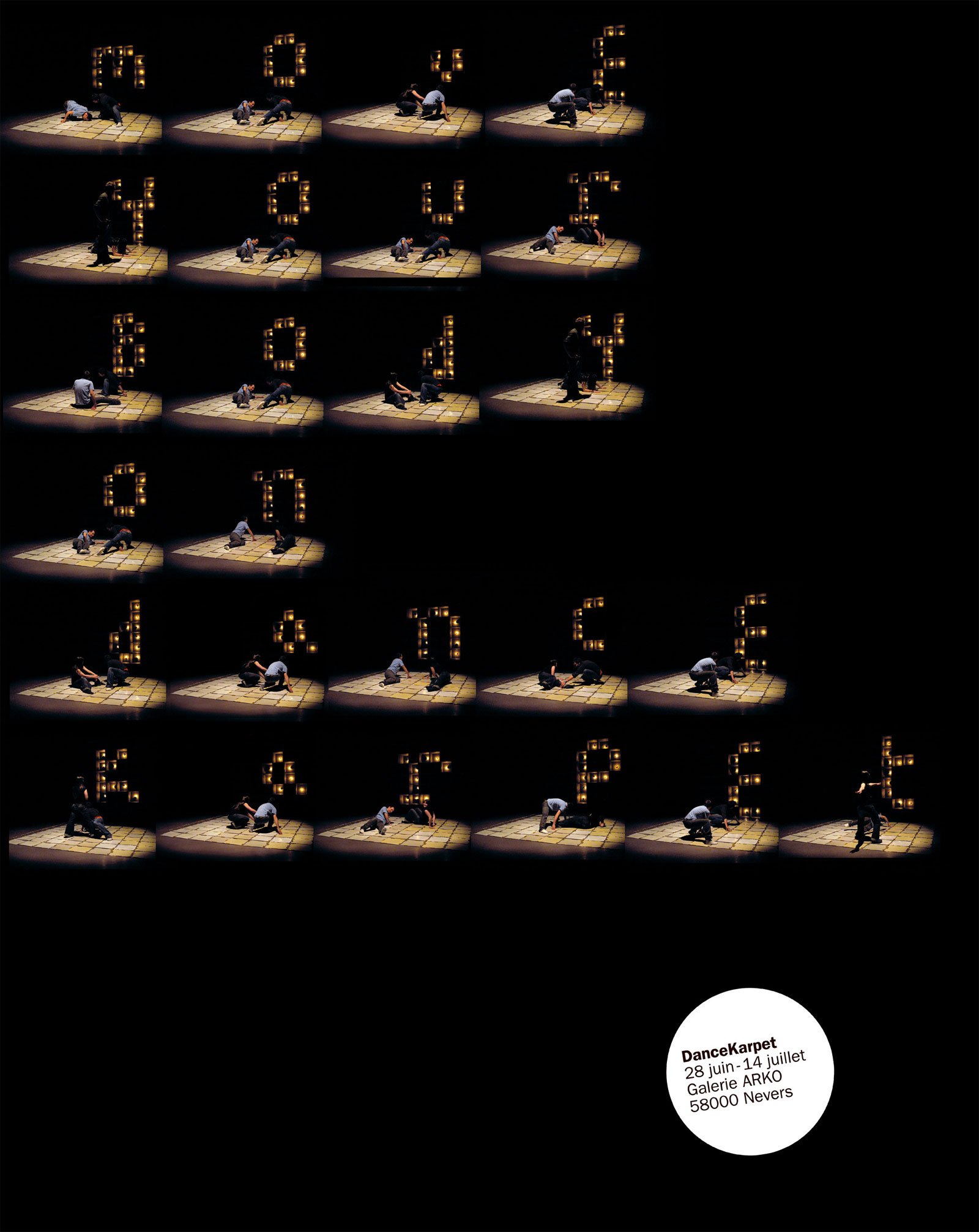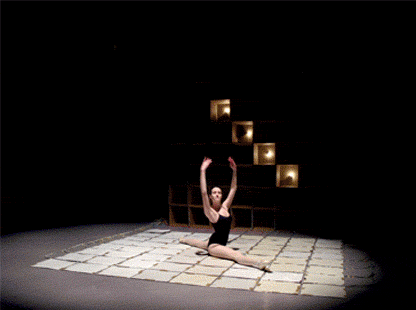
Think Experimental est un collectif de jeunes graphistes français. Le groupe se compose de Nicolas SIMON, Florian CHEVILLARD, Paul MALBURET et Thomas BERNARD. Tous sont diplômés en communication visuelle à l’École Supérieure d’Arts Appliqués de Bourgogne (ESAAB) située à Nevers. Formé en 2005, le collectif explore divers domaines des arts visuels privilégiant une approche expérimentale. Aux influences multiples, il est difficile de définir un style graphique au groupe tant leurs travaux sont variés. Chaque création est la rencontre de quatre sensibilités différentes. Cependant, la valorisation de l’accident graphique, la mise en avant du processus créatif et l’utilisation d’outils inhabituels apparaissent régulièrement dans leur travail. Passionné, le collectif cherche néanmoins la qualité et l’exigence dans son travail. L’aspect sémantique tient également une place importante dans chaque projet. Le collectif revendique dans la profession de graphiste un savoir-faire aussi bien conceptuel que technique.